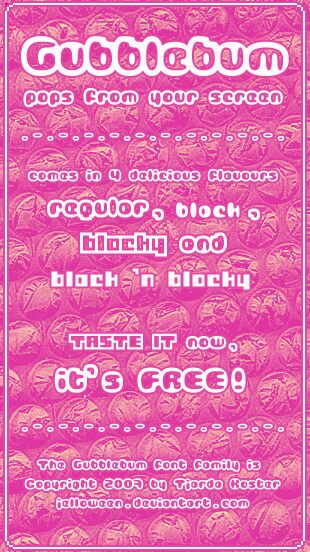
Gubblebum Blocky autorstwa Tjardy Koster to darmowy, geometryczny font typu display z konturowymi znakami, utrzymany w zabawnym klimacie ery bitmap. Litery zbudowane są z masywnych, prostych kątów i kwadratowych wycięć, co nadaje krojowi rytm przypominający klocki – efekt jest bezpośredni, przyjazny i ma w sobie retro luz, zamiast surowości.
Sprawia to, że font ten idealnie nadaje się do logotypów gier, opakowań dla dzieci, nagłówków plakatów, okładek zinów i plansz tytułowych, gdzie krótkie słowa wymagają wyrazistego, modularnego charakteru. Jako darmowy font, świetnie sprawdzi się też na naklejkach, grafikach do streamów i przy szybkich próbach brandingu, zwłaszcza gdy zależy Ci na tym, by schodkowy kontur i pudełkowa dynamika same wykonały całą wizualną robotę.